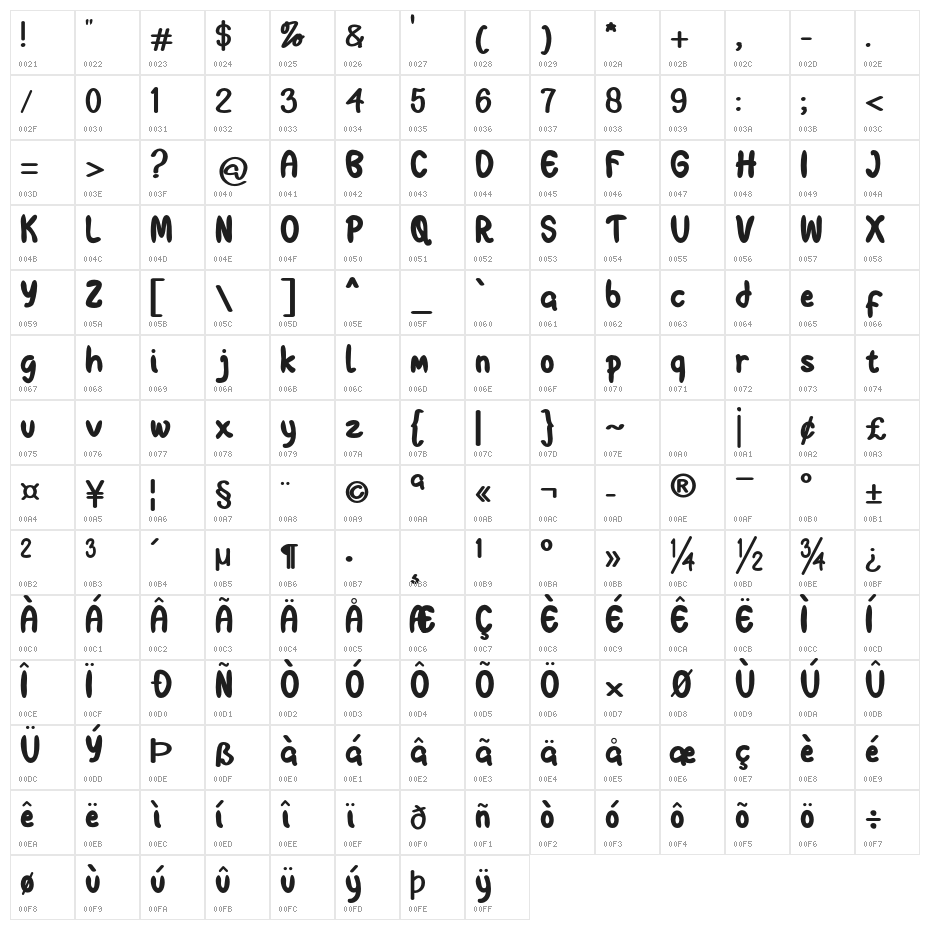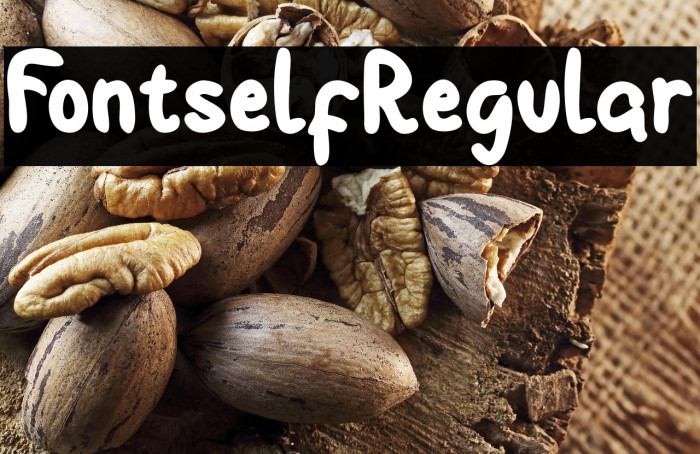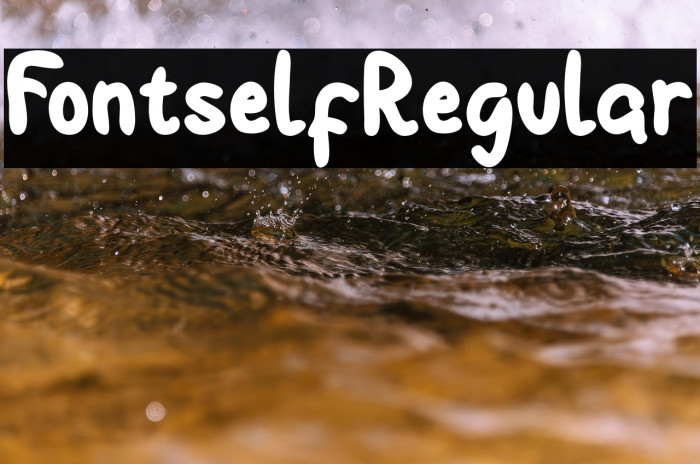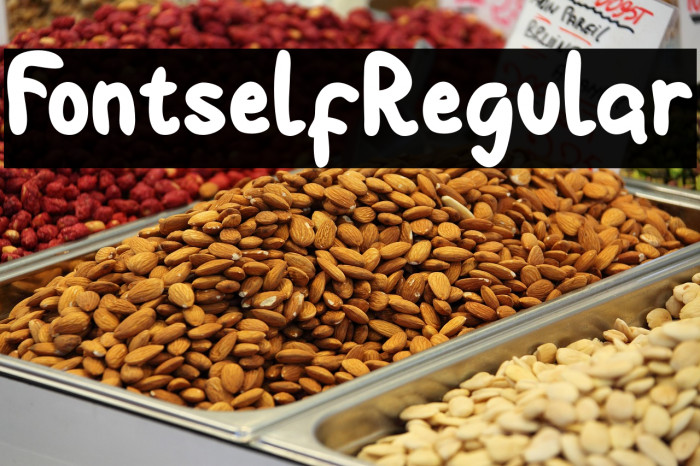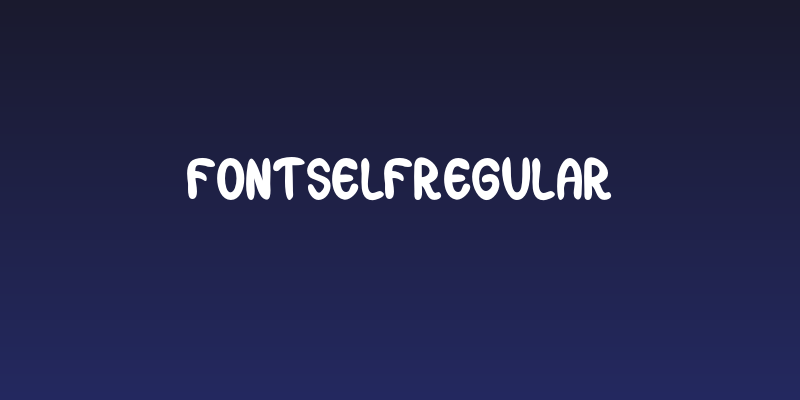
FontselfRegular Font
| Общий стиль | Playful |
| Область применения | Headlines, Logos, Informal Text |
| Рекомендуемые проекты | Ideal for children's books, greeting cards, playful branding, and social media graphics. |